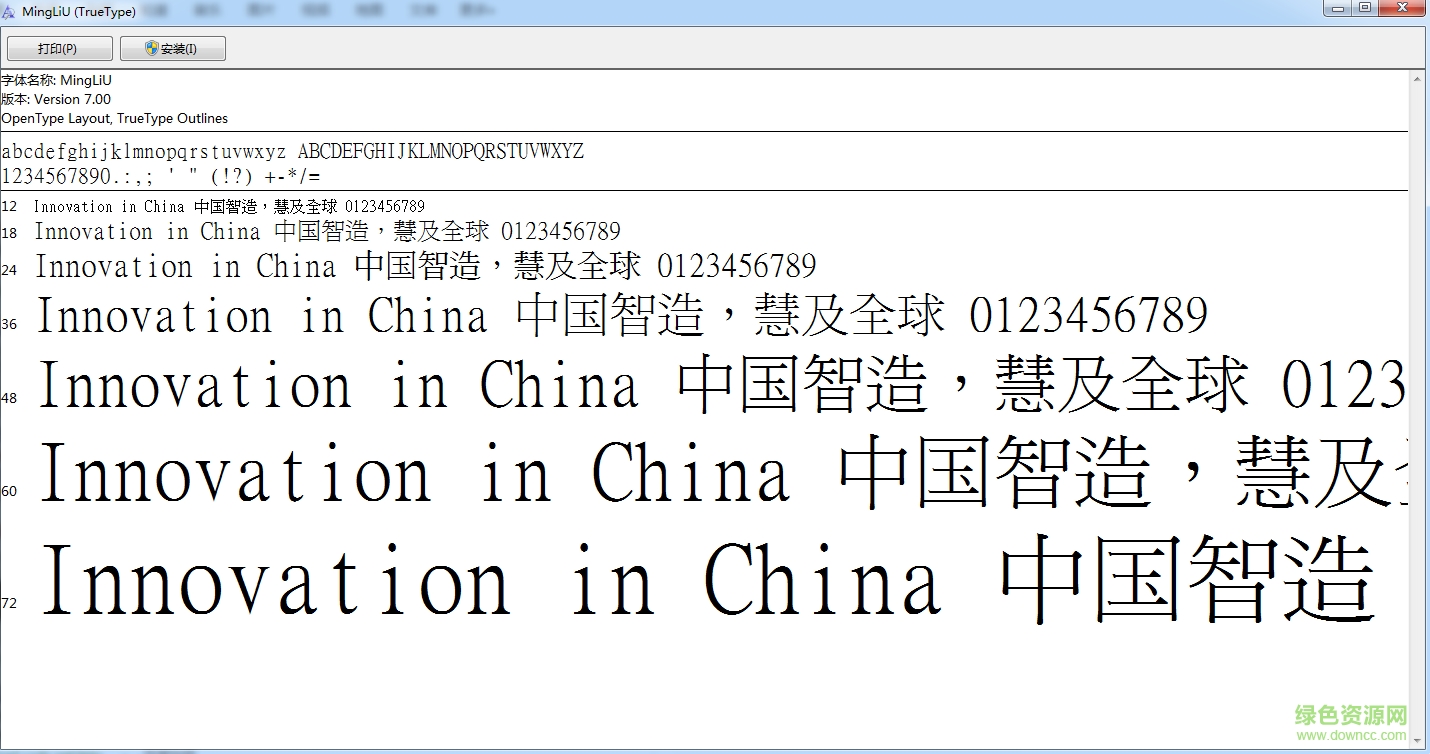
細明體字體簡體
細明體.ttf字體文件是一款由宋體演變而來的簡體中文字體,該字體保留了宋體的基本特征,工整耐看,結體嚴謹,整體效果古樸典雅,可用作文章排版或報刊正文等,歡迎大家免費下載!
細明體簡體介紹
細明體原來的字形非常接近傳統(tǒng)中文寫法,有些人稱之為康熙字典體;如取“靑”不取“青”、取“旣”不取“既”、取“為”不取“為”、取“兪”不取“俞”。但后來 Unicode 將這些字分開編碼,原碼位于是被俗字“青”、“既”、“為”取代。但部份使用這些字作部件的如“請”、“倩”等則維持不變。